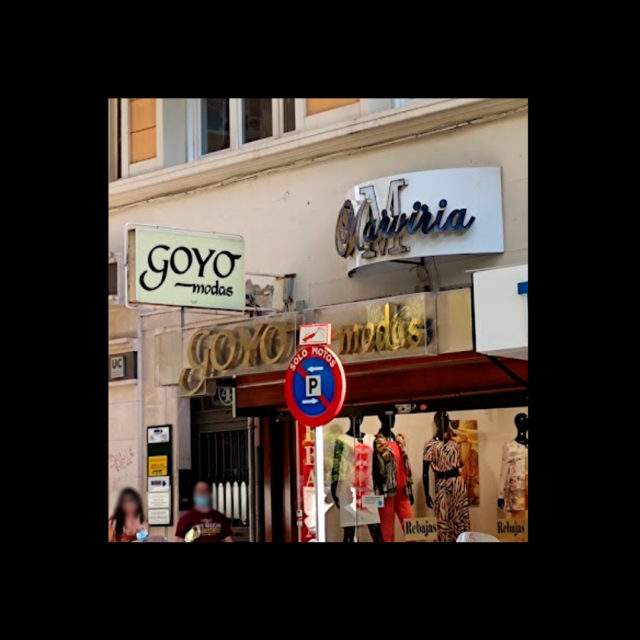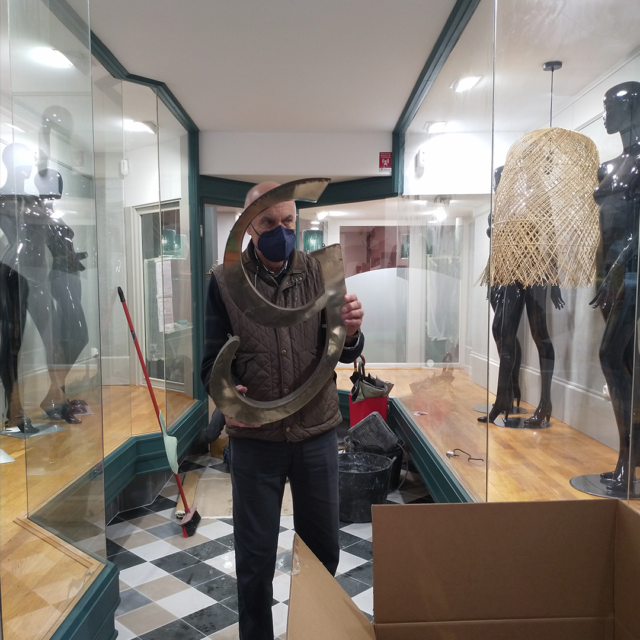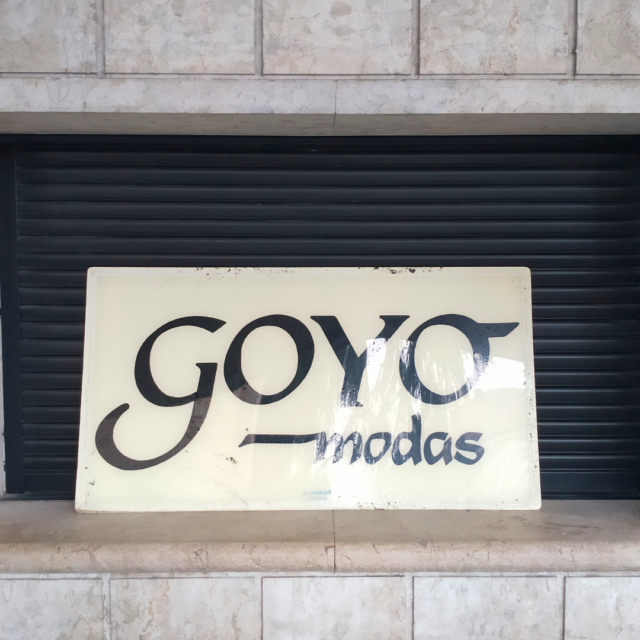
Goyo Modas
Hemos conseguido salvar este rótulo con más 40 años de historia de acabar en la basura. Gracias a los custodios del #PatrimonioGráfico, que están a pie de calle y a través de una llamada, hemos podido gestionar este rescate y por tanto, preservar estas planchas de metacrilato y las nueve letras de latón con tubos.